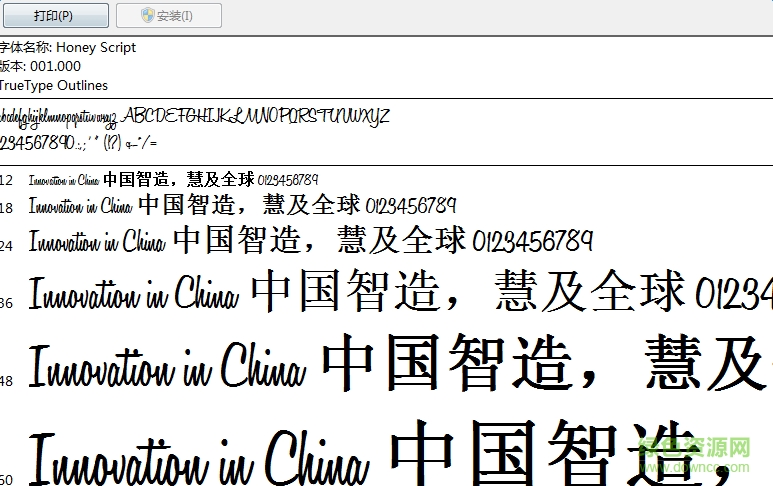
軟件介紹 軟件標簽: 英文字體 字體 honey script字體是一款英文字體庫中的個性字體,該字體可以廣泛應(yīng)用于廣告設(shè)計、宣傳海報、ppt、影視制作以及任何使用文字的領(lǐng)域,有需要的朋友可以免費下載收藏。字體安裝方法方法一:控制面板/字體/文件/安裝新字體;方法二:直接將字體復(fù)制到C:\WINDOWS\Fonts。方法三:針對win7系統(tǒng),用戶只需選中字體右鍵安裝即可。注意事項本站所有字體資源僅供個人學(xué)習(xí)與參考,如需商業(yè)使用請到相關(guān)官網(wǎng)授權(quán)。 軟件截圖 上一張下一張(1 / 1) 安裝詳細截圖 猜你喜歡 花體字體 花體字體 花體英文字體就相當(dāng)于國內(nèi)的書法字體,藝術(shù)性極高,這類字體通常筆劃連綿,線條如游絲,結(jié)構(gòu)精巧,變化精妙,總體來說裝飾性強于實用性! 查看更多>> alexbrush regular字體 33KB/中文/5.0/下載 brockscript字體 26KB/中文/10.0/下載 champignon-普通(西方)字體 20KB/中文/10.0/下載 freebooter script 32KB/中文/10.0/下載 italianno regular 60KB/中文/0.0/下載 beautifules字體 39KB/中文/0.0/下載 其他版本下載 標題 大小 更新日期 下載 下載地址 電腦版 honey script light字體 點擊報錯 軟件無法下載或下載后無法使用,請點擊報錯,謝謝! 關(guān)閉報錯反饋 請描述您所遇到的錯誤,我們將盡快予以修正,謝謝! *必填項,請輸入內(nèi)容 本類最新 sounso beauty字體 spyced哥特英文字體 ttf版 zerodegrees字體 the next font ttf版 coolvetica font keep calm ttf 免費版 相關(guān)文章 Photoshop字體安裝使用方法和技巧 如何解決“無法新增字體”問題 Win 7系統(tǒng)安裝字體方法 網(wǎng)頁字體大小設(shè)置方法 怎么改網(wǎng)頁字體大小 在Linux系統(tǒng)中安裝字體的幾種方法 windows7字體顯示問題:打開某些程序的時候顯示的是亂碼 用戶評論 熱門評論 最新評論 發(fā)表評論 查看所有評論(0) 昵稱: 請不要評論無意義或臟話,我們所有評論會有人工審核. 字數(shù): 0/500 (您的評論需要經(jīng)過審核才能顯示)